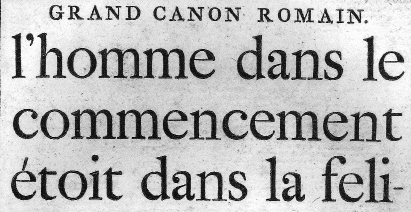
Jacques François Rosart (1714–1777) werd in Namen geboren. Deze stad was economisch welvarend totdat zij in 1713 in Hollandse handen kwam, want toen ging het met de handel snel bergafwaarts. Rosart, die zichzelf het vak van stempelsnijder had geleerd, vestigde zich daarom in 1740 in Haarlem. Drie jaar later kocht de firma Enschedé, die al zo'n veertig jaar als drukkerij in Haarlem was gevestigd, de lettergieterij van Wetstein in Amsterdam, en verhuisde de inventaris naar Haarlem. Niet alleen bestond een deel hiervan uit stempels en matrijzen van Johann Michael Fleischmann, maar Fleischmann zèlf zou de daarop volgende vijfentwintig jaar voor Enschedé werken. De enkele opdracht die Rosart van Enschedé kreeg, woog niet op tegen de concurrentie die hij van dezelfde firma te duchten kreeg.
Rosart ging failliet, beproefde elders in Nederland zonder succes zijn geluk en week uiteindelijk uit naar Brussel. Daar gelukte het hem om in 1759 alsnog een succesvolle lettergieterij op te zetten.
In 1761 en 1768 produceerde Jacques François Rosart een letterproef, Eupreuve des caracteres, Qui se gravent & fondent dans la nouvelle fonderie de Jacques François Rosart. Eén van de drie exemplaren van de 1768-proef uit de collectie van de Koninklijke Bibliotheek te Brussel heeft de Dutch Type Library integraal gescand. De scans vormen mede de basis van de digitale revival waaraan Antoon de Vijlder momenteel werkt.
Ampersand Rosart
Grand Canon Romain